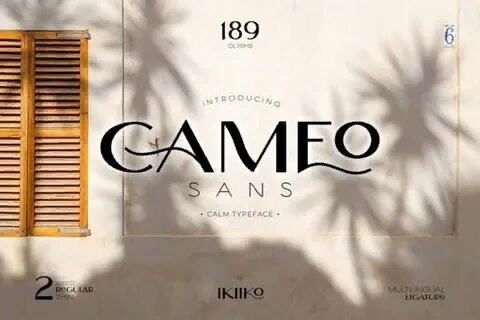
[Creativefabrica] Cameo Font (2021)
Название: Cameo Font (2021)
Cameo - элегантный, волнистый и нежный шрифт без засечек.
Влюбитесь в его невероятно универсальный стиль и используйте его для создания эффектных дизайнов!